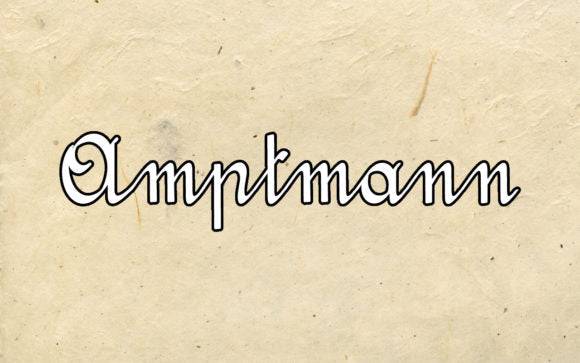
Fuente Amptmann Script para invitaciones, citas y tarjetas de felicitación
Amptmann Script es una fuente caligráfica fluida que aporta elegancia e intimidad a tus diseños. Perfecta para proyectos personales y emotivos, esta fuente presenta curvas naturales y trazos caligráficos, ideales para invitaciones, citas y tarjetas.
Esta fuente captura la sensación de una escritura fina con un ritmo y una legibilidad consistentes. Ya sea para papelería impresa o mensajes digitales, Amptmann Script le ayuda a expresar calidez y personalidad mediante una tipografía hermosa.
Es una opción ideal para proyectos que requieren tonos románticos, festivos o emotivos, realzando piezas de comunicación tanto informales como formales.
Por qué te encantará
- Elegancia manuscrita con curvas suaves.
- Perfecto para diseños sentimentales y formales.
- Funciona bien tanto en formato impreso como digital.
- Gran legibilidad con detalles expresivos.
P: ¿Qué tipo de fuente es Amptmann Script?
A: Amptmann Script es una fuente estilo script que imita la escritura a mano elegante, perfecta para aplicaciones de diseño personal, romántico o formal.
P: ¿Esta fuente se verá bien en tarjetas impresas?
R: Por supuesto. Fue creado pensando en tarjetas de felicitación, impresiones e invitaciones, y se ve de maravilla en alta resolución.